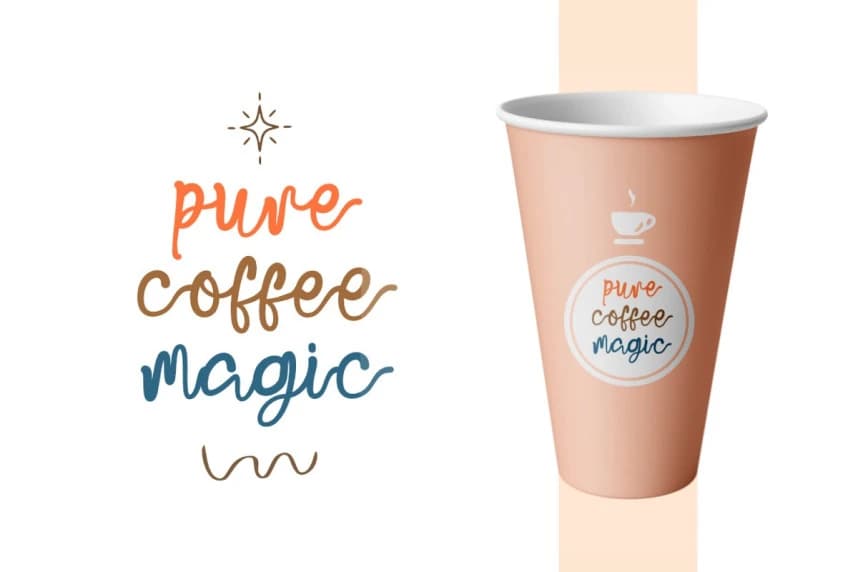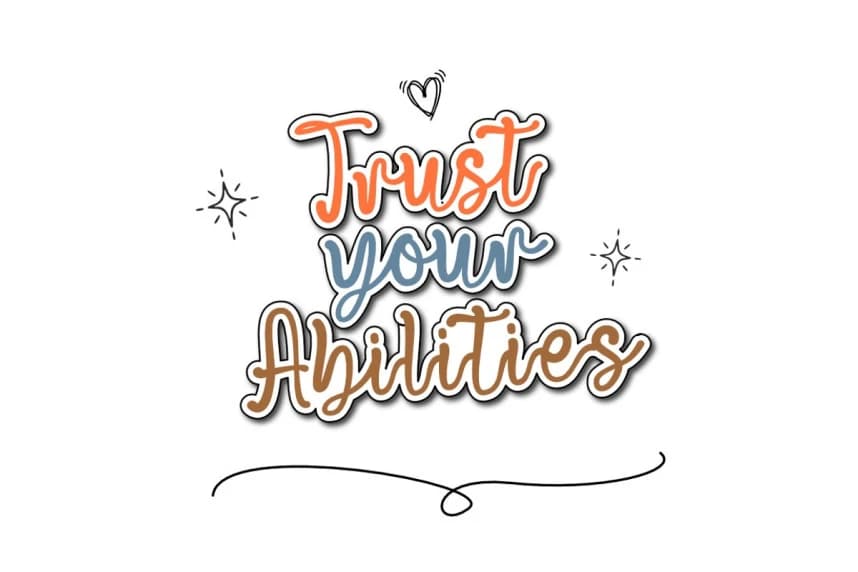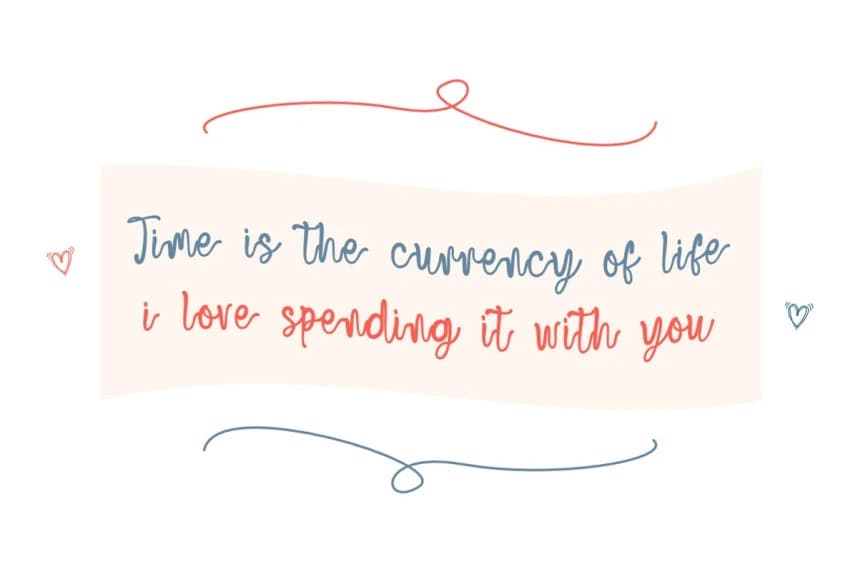
Bouncy Scribble Font
Bouncy Scribble Font, organik ve modern hissi veren keyifli bir el yazısı fontudur. Zıplayan bir temel çizgi ve tutarlı, akıcı darbelerle tasarlanmıştır. İster sosyal medya alıntıları hazırlıyor olun, ister modaya uygun giysiler tasarlıyor olun, logo
Bouncy Scribble Font, hem organik hem de modern hissi veren keyifli bir el yazısı fontudur. Dalgalı bir temel çizgisine ve tutarlı, akıcı çizgilere sahip olarak tasarlanmıştır. Sosyal medya paylaşımları için alıntılar yapıyor olsanız da, trend kıyafetler tasarlıyor olsanız da, logo